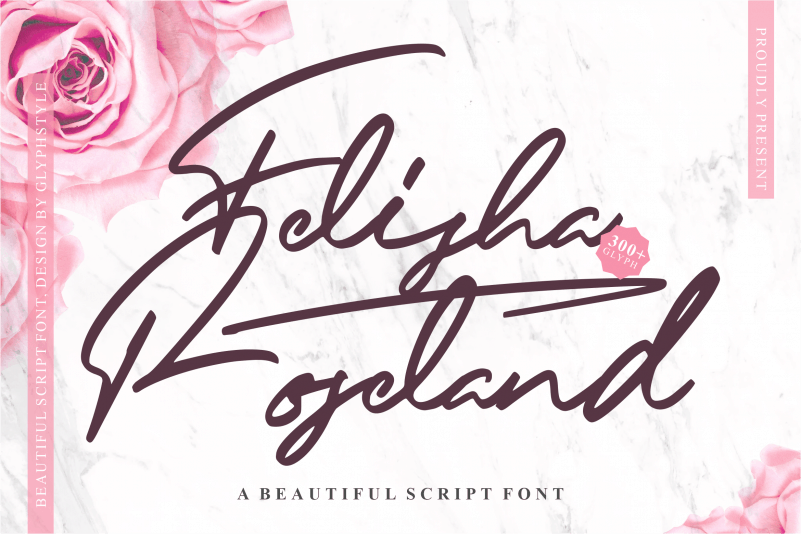
Felisha Roseland Script Font – Download Grátis
Felisha Roseland Script Font é uma elegante caligrafia escrita a mão que oferece uma sensação suave e natural. Esta fonte traz linhas delicadas e curvas perfeitas, transmitindo um toque de beleza e autenticidade que se assemelha à própria mão do autor. É ideal para aplicar em nomes de marca, nome próprio ou qualquer outra necessidade de design. Suas curvas suaves e sua aparência natural proporcionam uma textura única que pode revolucionar a maneira como você representa seus projetos. Com seu designer inconfundível da GlyphStyle, Felisha Roseland se destaca entre as outras fontes do tipo.